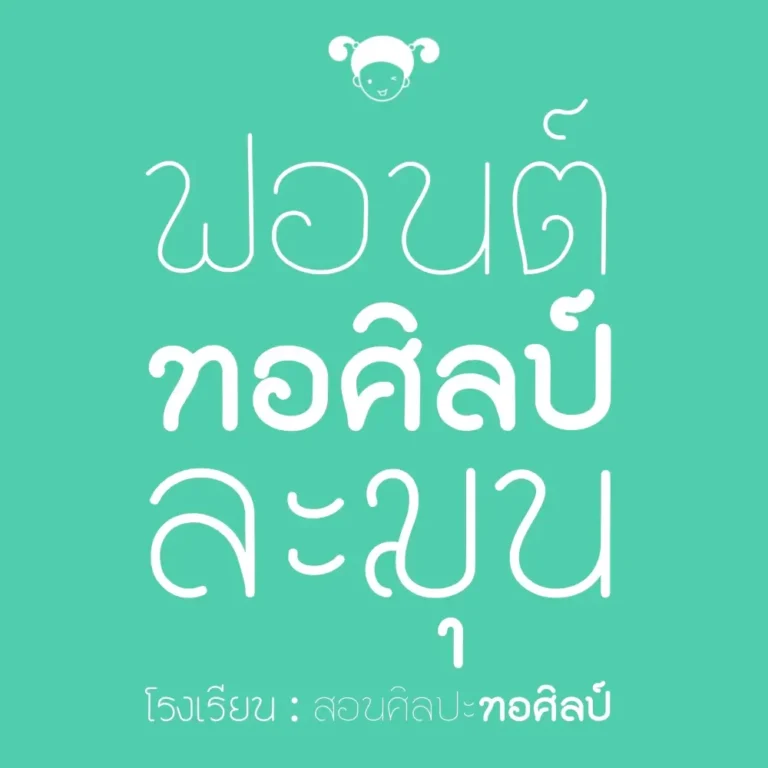
เป็นลายมือเขียนไว้เพื่อเอาไปใช้ตามโปสเตอร์ของโรงเรียนสอนศิลปะทอศิลป์ เลยเอามาทำเป็นฟอนต์เพื่อแจกฟรีให้ใช้โดยไม่มีเงื่อนไขครับผม
ฟอนต์โดย : ระจัน โรงเรียนสอนศิลปะทอศิลป์
Torsilp HiHi